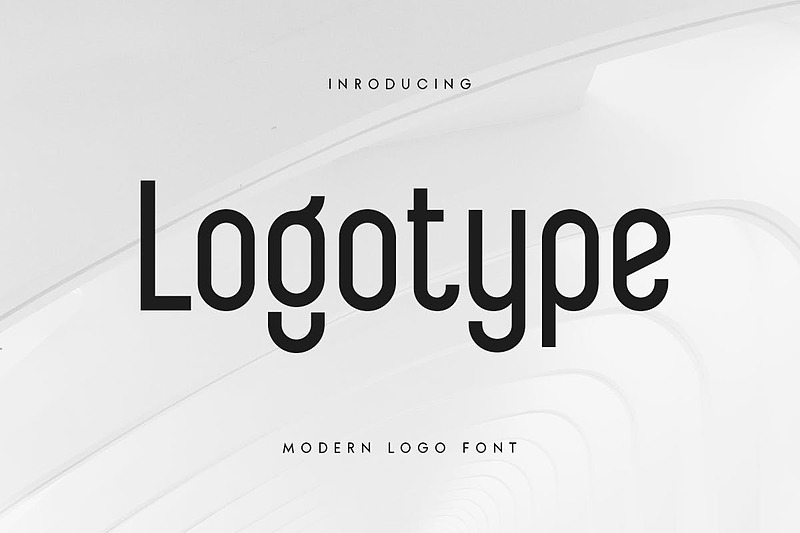
فونت انگلیسی لوگوتایپ مدرن (Logotype)
معرفی فونت لوگوتایپ
لوگوتایپ، فونت سنس سریف مدرن لوگوی خاص که به‌طور ویژه برای نیازهای برندسازی حرفه‌ای و مدرن خلق شده است. این فونت با کاراکترهای جایگزین با اشکال منحصربه‌فرد، ظاهری جذاب و متمایز را به برند شما هدیه می‌دهد. طراحان یا صاحبان محصولاتی که به دنبال راه‌حل‌هایی برای حرفه‌ای‌تر و مدرن‌تر کردن طراحی‌های خود هستند، می‌توانند به راحتی از این فونت استفاده کنند. ما برای این فونت کاراکترهای آلترنیت مختلفی تدارک دیده‌ایم تا به شما در ایجاد تنوع بی‌نهایت برای نیازهای خلاقانه‌تان کمک کنیم.
فونت لوگوی مدرن لوگوتایپ با امکانات زیر آماده است:
• گزینه‌های متعدد برای ایجاد تغییرات خلاقانه (ترکیب‌های آلترنیت‌ها)
• پیش‌نمایش الهام‌بخش برای نشان دادن امکانات فونت
• شامل حروف کوچک و بزرگ
• اعداد و علائم نگارشی و پشتیبانی چندزبانه
• طبقه‌بندی: سنس سریف